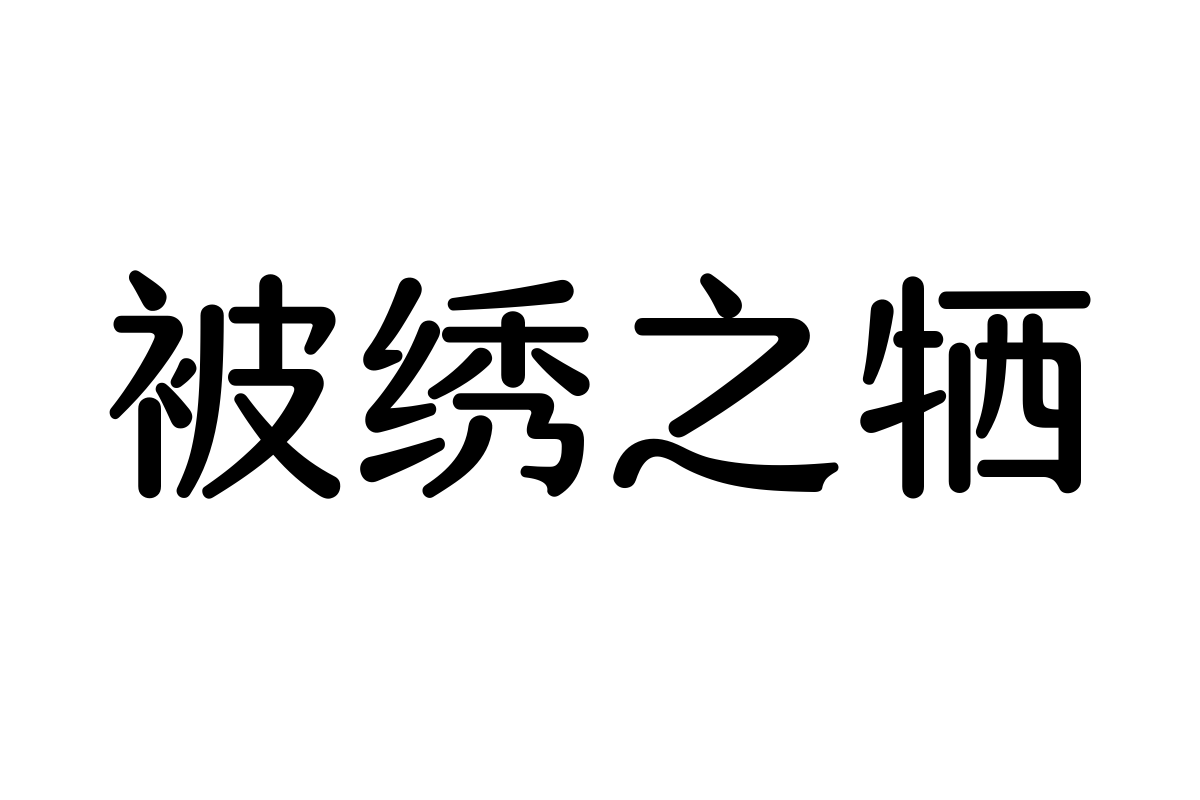
汉仪清雅体简是一套专为中文排版设计的字体,具有优雅、简洁的风格。它由汉仪字库公司开发,旨在为用户提供高质量的文字显示效果。
该字体的特点如下:
1. 风格独特:汉仪清雅体简的字形线条流畅,结构紧凑,给人一种清新、高雅的感觉。
2. 适用范围广:无论是用于报纸、杂志、书籍还是网页设计,汉仪清雅体简都能展现出其独特的魅力。
3. 易读性强:该字体的笔画粗细适中,易于阅读和辨认,适合各种场合使用。
汉仪清芬体的笔画粗细适中,既有力度又不失柔和,使得整个字体看起来既庄重又不失灵动。其独特的结构设计,使得每个字都显得饱满而有力,同时也保留了一定的空间感,使得整体视觉效果更加和谐。
此外,汉仪清芬体还注重细节的处理,无论是笔画的连接处还是字符之间的间距,都经过精心设计,使得整款字体看起来既美观又易读。这使得它在各种应用场景中都能够发挥出出色的效果,深受设计师们的喜爱。